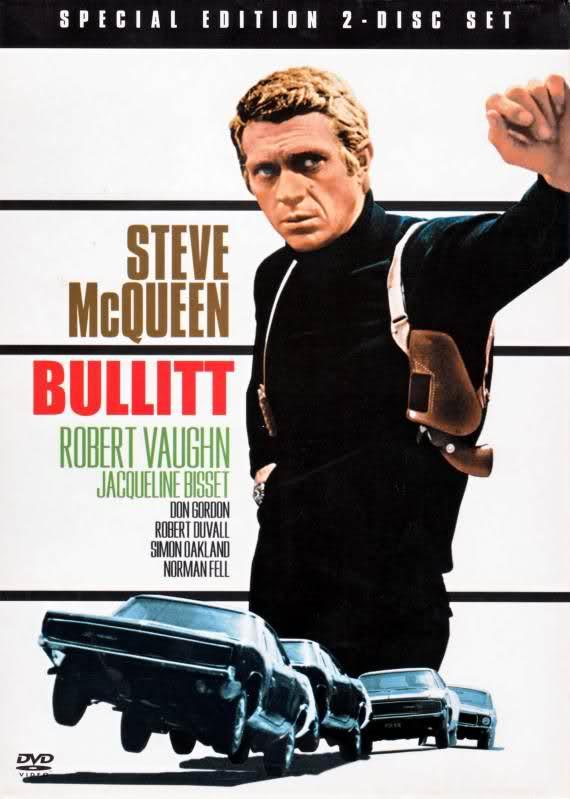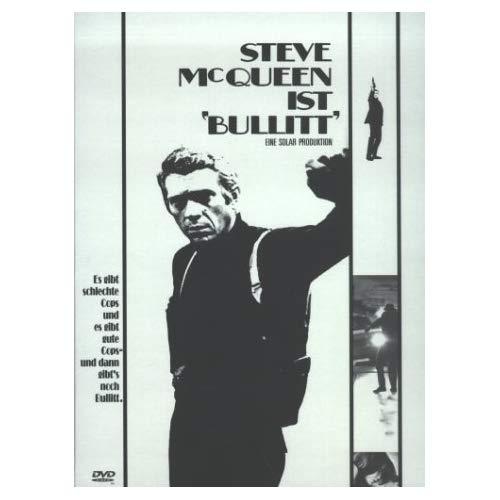
kann mir jemand sagen, welche Schriften hier verwendet wurden.
geht so in diese Richtung ... aber das müsste doch auch noch mit ganz engen Schnitten von »normaleren« Schriften gehen, oder?
danke, die Compacta isses.
Die grüne Schrift scheint ne andere zu sein, da die Kurve beim S
schon extrem ist.